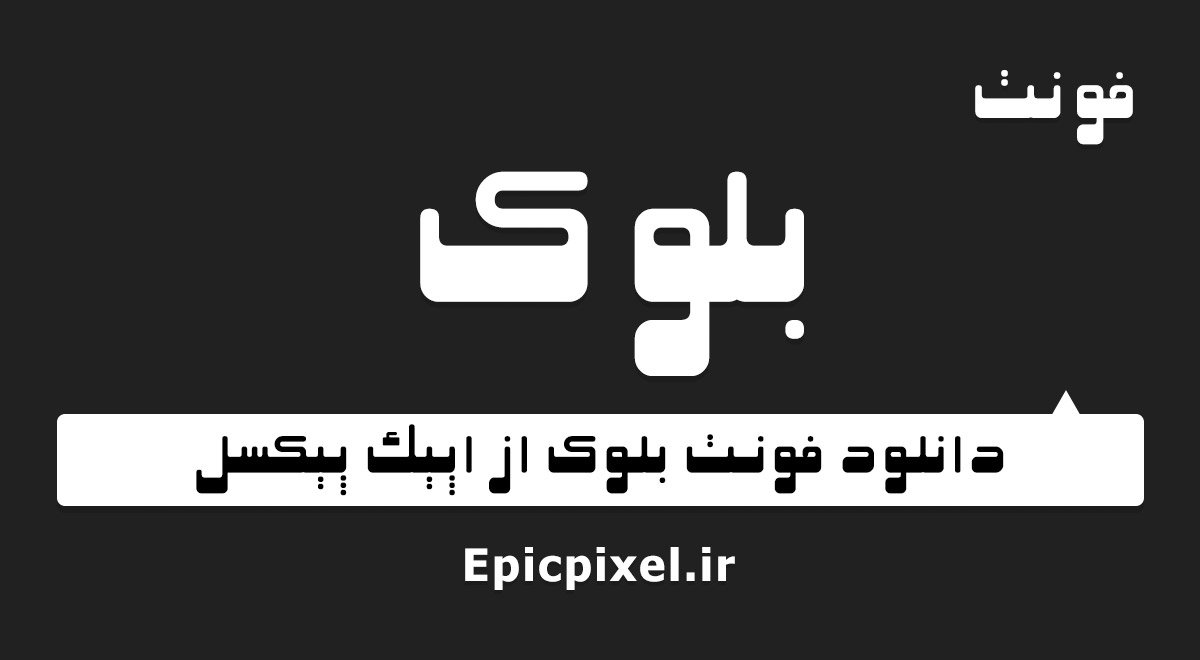
4 فونت بلوک فارسی Block
فونت بلوک فارسی، یک انتخاب خاص برای طراحانی است که به دنبال فونتی مدرن و متمایز هستند. این فونت با ساختاری هندسی و استفاده از بلوک های مربع و مستطیل طراحی شده و ظاهری منحصربه فرد به آن بخشیده است. اگر به دنبال فونتی هستید که در عناوین کوتاه و سنگین، جلوه ای چشمگیر داشته باشد، بلوک گزینه ای ایده آل است.